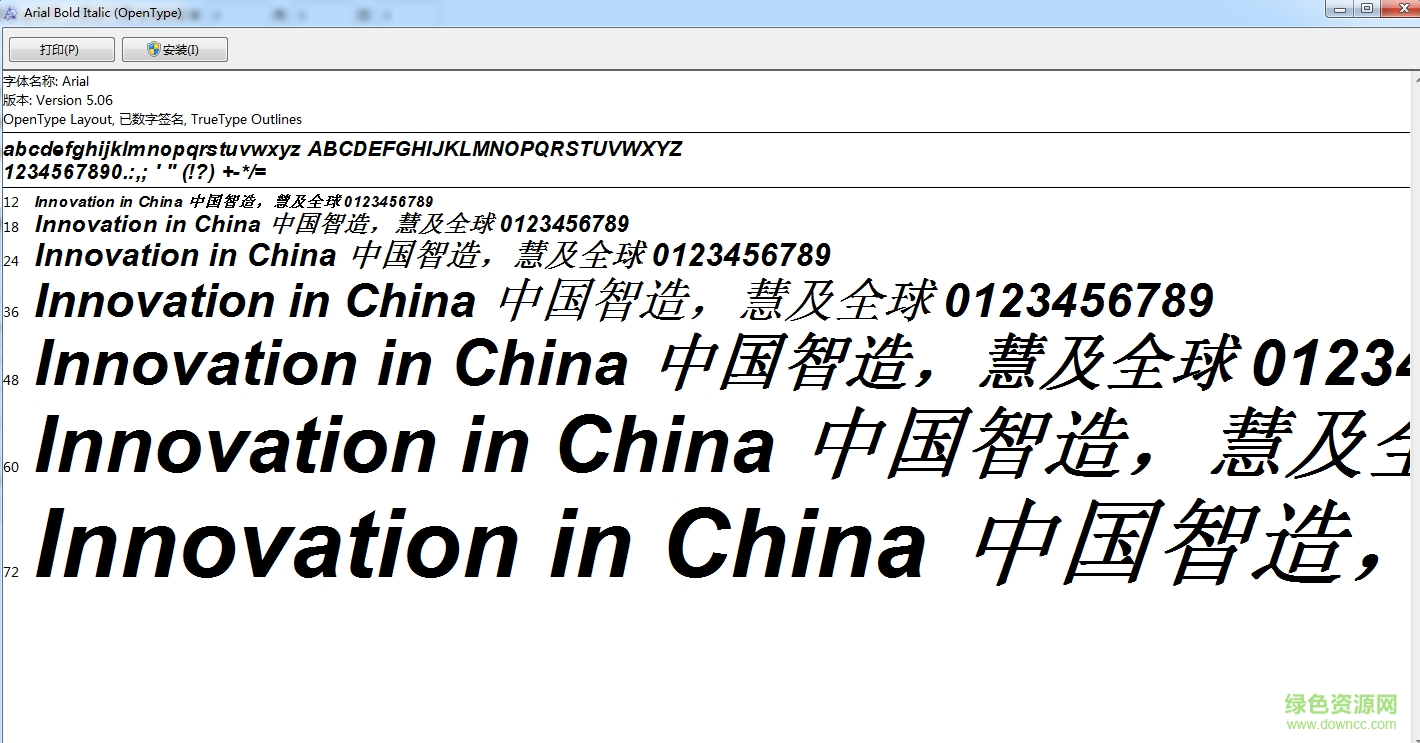
arial bold italic字體是一款粗黑的斜體字體,字體線條勻稱,布局嚴謹,筆觸和諧統(tǒng)一,辨識度高,可應(yīng)用的領(lǐng)域非常廣泛,歡迎大家在綠色資源網(wǎng)下載!
意大利體起源于手寫體,16世紀初在意大利威尼斯就已經(jīng)出現(xiàn)為節(jié)省版面的斜體。由于起源于手寫體,字形向右傾斜是其最大特征。最初是與正文完全不同的獨立字體出現(xiàn)的,現(xiàn)在電腦字體中已經(jīng)作為在襯線體字體的一部分收入,在正體排版中需要強調(diào)、區(qū)別的時候使用。